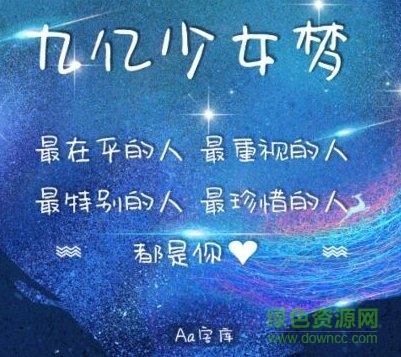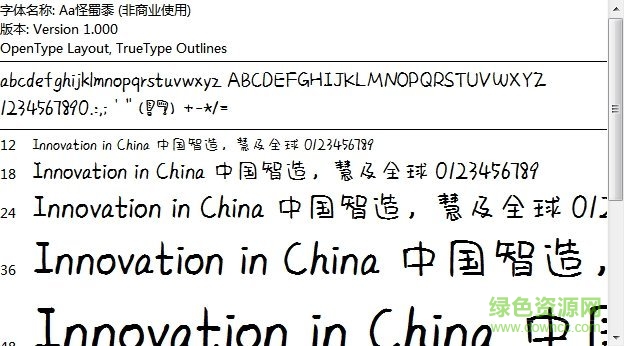
Aa九億少女夢字體
九億少女夢字體是一款溫柔清秀的少女字體,也叫aa怪蜀黍字體,是專為林狗設(shè)計的手寫字體,干凈而溫婉,有著少女懷春的夢幻體驗(yàn),快來綠色資源網(wǎng)下載收藏吧!
Aa九億少女夢字體介紹
你是我的可遇不可求,可遇不可留
最在乎的你,最重視的人,最熱別的人,最珍惜的人
都是你